Wenn man Texte liest, egal ob auf dem Handy, im Buch oder auf einer Website, sieht man immer Schriftarten. Manche wirken modern, manche alt, manche wie Handschrift. Viele Menschen fragen sich deshalb: Welche Schriftarten gibt es eigentlich? Und wie viele davon existieren weltweit?
In diesem Artikel erkläre ich das ganz einfach. Keine schweren Wörter, kein Fachchinesisch. Nur klare Erklärungen mit echten Beispielen, so wie man es jemandem persönlich erklären würde.
Welche Schriftarten gibt es?
Es gibt sehr viele Schriftarten, aber keine Sorge – man muss sie nicht alle kennen. Die meisten Schriftarten lassen sich in ein paar Hauptgruppen einteilen. Diese Gruppen helfen uns zu verstehen, welche Schrift wofür benutzt wird.
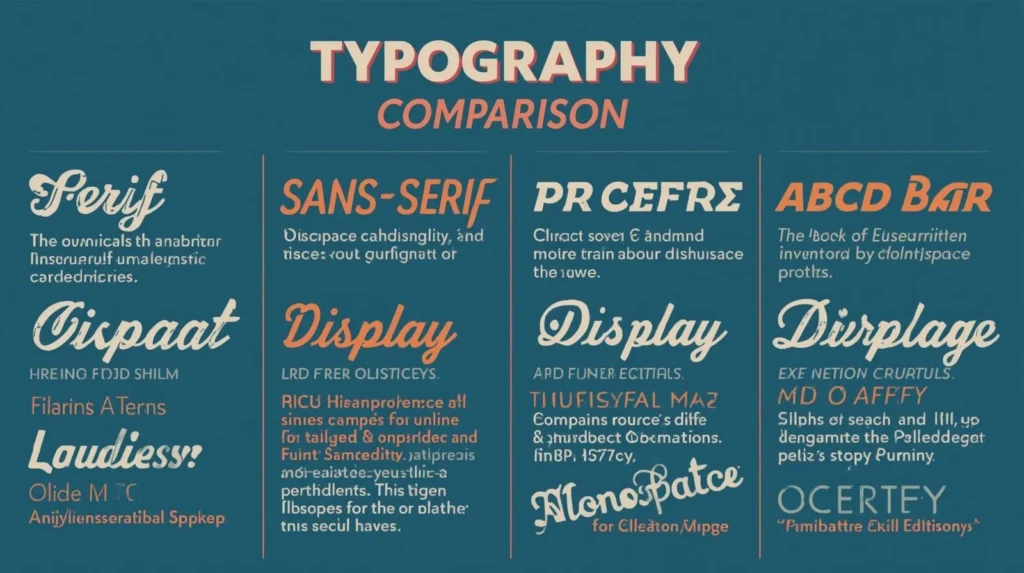
Serifenschriften (Antiqua)
Serifenschriften erkennt man an den kleinen Füßchen an den Buchstaben. Diese kleinen Linien sitzen oft am Anfang oder Ende eines Buchstabens.
Diese Schriftarten wirken:
- klassisch
- ruhig
- seriös
Man findet sie oft in:
- Büchern
- Zeitungen
- langen Texten
Bekannte Beispiele:
- Times New Roman
- Garamond
- Baskerville
Viele Menschen empfinden Serifenschriften als angenehm beim Lesen, besonders bei langen Texten auf Papier.
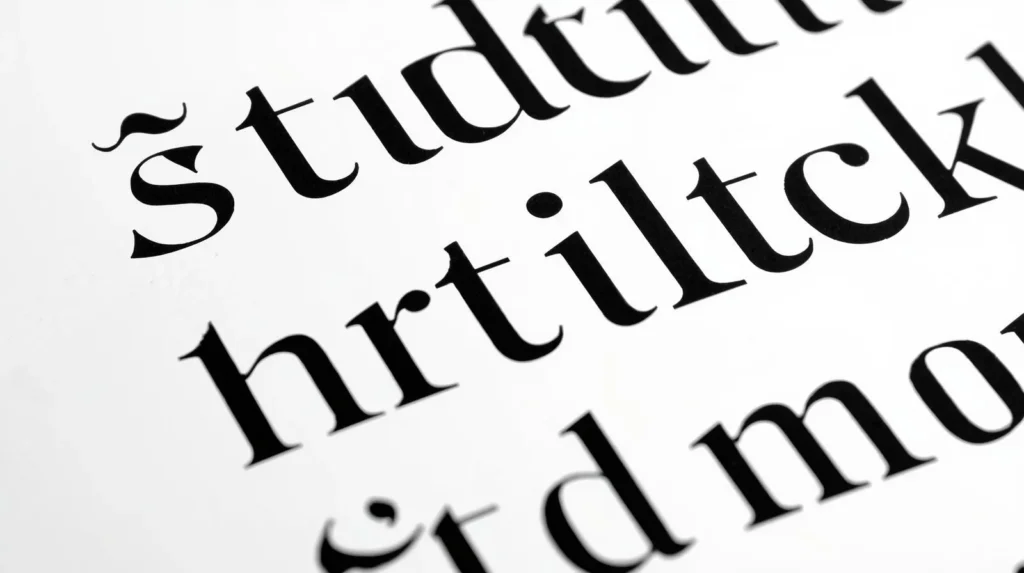
Serifenlose Schriftarten (Sans Serif)
Serifenlose Schriftarten haben keine Füßchen. Die Buchstaben sehen sauber und gerade aus.
Diese Schriftarten wirken:
- modern
- klar
- einfach
Sie werden häufig benutzt auf:
- Websites
- Smartphones
- Apps
Bekannte Beispiele:
- Arial
- Helvetica
- Calibri
- Roboto
Im Internet sind serifenlose Schriftarten sehr beliebt, weil sie auf Bildschirmen gut lesbar sind.
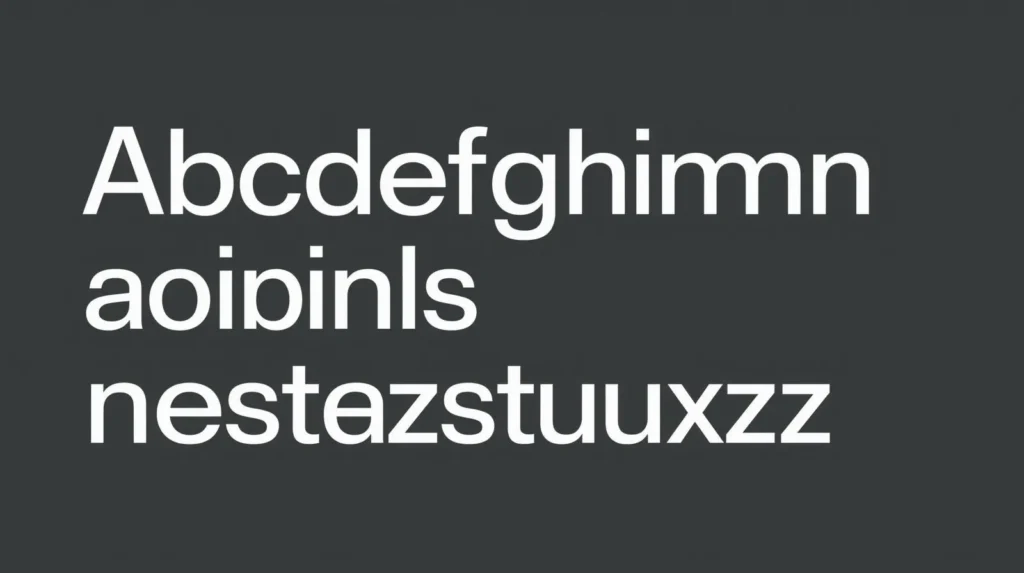
Schreibschriften (Handschrift)
Schreibschriften sehen so aus, als hätte jemand sie mit der Hand geschrieben. Manche sind locker, manche elegant.
Diese Schriftarten wirken:
- persönlich
- kreativ
- freundlich
Man nutzt sie oft für:
- Einladungen
- Karten
- besondere Designs
Bekannte Beispiele:
- Brush Script
- Pacifico
Für lange Texte sind sie eher ungeeignet, aber für kurze Überschriften oder Dekorationen sind sie sehr beliebt.
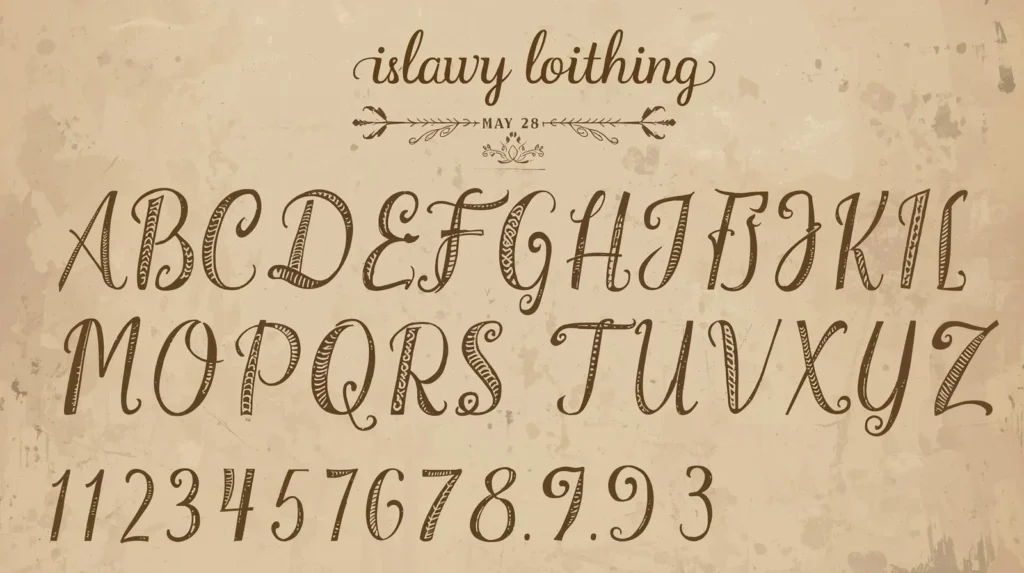
Display- und dekorative Schriftarten
Diese Schriftarten fallen sofort auf. Sie sind oft auffällig, verspielt oder kreativ.
Sie werden verwendet für:
- Logos
- Plakate
- Überschriften
Beispiele:
- Monoton
- Lobster
Für normale Texte sind sie nicht gut geeignet, aber für Design-Zwecke sind sie perfekt.
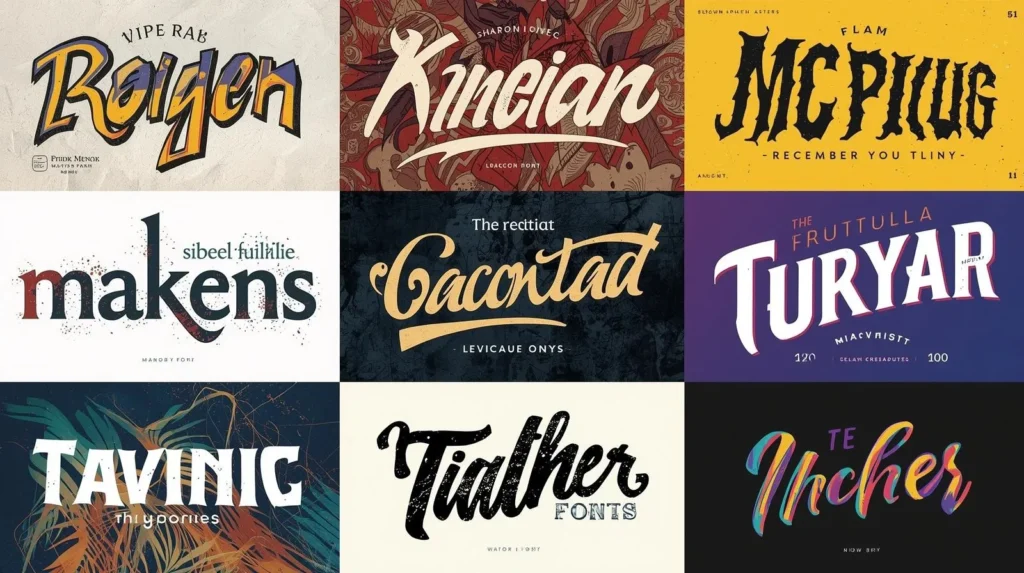
Monospace-Schriftarten
Bei Monospace-Schriftarten hat jeder Buchstabe die gleiche Breite. Das bedeutet: ein „i“ nimmt genauso viel Platz ein wie ein „m“.
Diese Schriftarten wirken:
- technisch
- ordentlich
- gleichmäßig
Man findet sie oft bei:
- Programmier-Code
- alten Schreibmaschinen-Texten
- technischen Anzeigen
Bekanntes Beispiel:
- Courier New
Für normales Lesen sind Monospace-Schriften nicht ideal, aber für Computer und Technik sind sie sehr praktisch.
Wie viele Schriftarten gibt es?
Eine genaue Zahl gibt es nicht. Jeden Tag kommen neue Schriftarten dazu. Designer auf der ganzen Welt erstellen ständig neue Fonts.
Man kann aber sagen:
- Es gibt tausende verschiedene Schriftarten
- Jedes Jahr entstehen viele neue
- Alte und neue Schriftarten existieren nebeneinander
Deshalb ändert sich die Anzahl ständig.
Wie viele Schriftarten gibt es auf der Welt?
Weltweit gibt es Schriftarten für:
- lateinische Sprachen
- arabische Sprachen
- asiatische Sprachen
- viele weitere Schriftsysteme
Wenn man alle Länder und Sprachen zusammenzählt, gibt es sehr viele zehntausend Schriftarten. Eine feste Zahl ist nicht möglich, weil ständig neue erstellt werden.
Welche Schriftarten werden häufig verwendet?
Einige Schriftarten sieht man besonders oft, weil sie:
- gut lesbar sind
- auf fast jedem Computer vorhanden sind
Sehr häufig verwendet werden:
- Arial
- Times New Roman
- Helvetica
- Calibri
Diese Schriftarten werden in Schulen, Büros, auf Webseiten und in Dokumenten genutzt.
Was gibt es für Schriftarten im Alltag?
Im Alltag begegnen uns viele Schriftarten:
- auf dem Handy
- auf Webseiten
- in Apps
- in Büchern
Meist merken wir gar nicht, welche Schriftart wir gerade lesen. Trotzdem beeinflusst sie, wie angenehm ein Text wirkt.
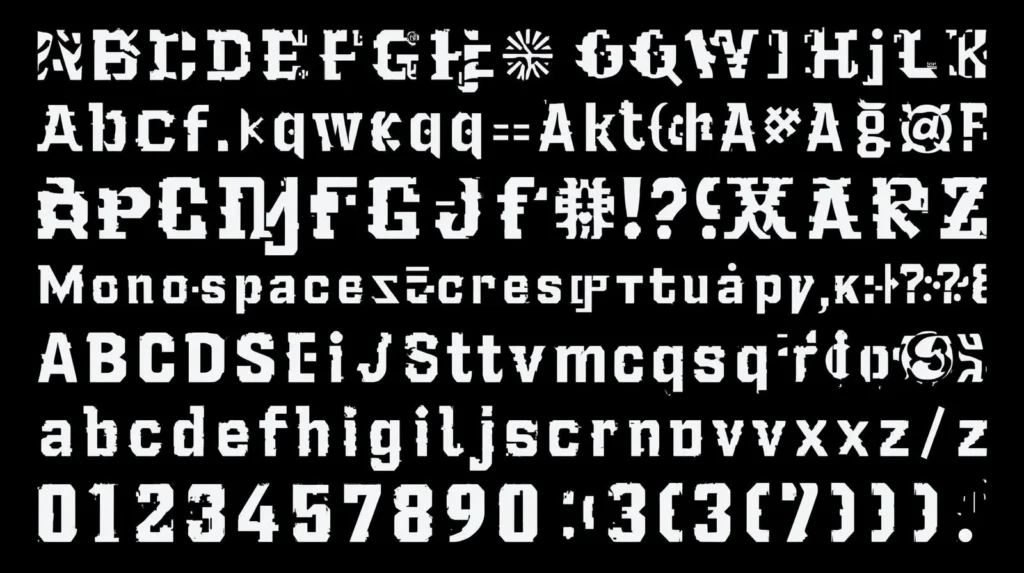
Kurze Übersicht der wichtigsten Schriftarten
| Schriftart-Typ | Typische Nutzung |
| Serif | Bücher, Zeitungen |
| Sans Serif | Webseiten, Apps |
| Handschrift | Karten, Designs |
| Display | Logos, Plakate |
| Monospace | Programmierung |
Fazit
Es gibt viele verschiedene Schriftarten auf der Welt. Jede Schriftart hat ihren eigenen Stil und Zweck. Manche sind besser für lange Texte, andere für Design oder Technik.
Wer Schriftarten versteht, kann Texte schöner, klarer und passender gestalten. Es lohnt sich also, ein wenig darauf zu achten, welche Schrift man verwendet.